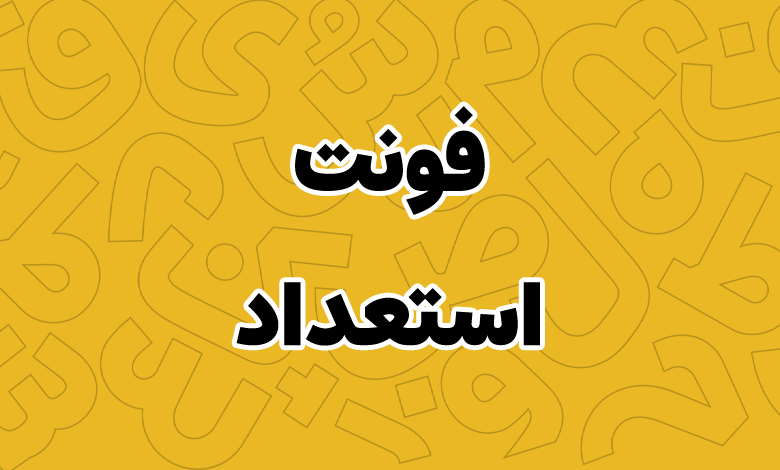
فونت استعداد (Estedad)
فونت استعداد (به انگلیسی: Estedad) در گروه فونتهای رایگان و مناسب متنهای طولانی قرار دارد. این فونت خانوادهدار از چندین وزن متنوع پشتیبانی میکند که به منظور بهینهسازی برای استفاده در متنهای طولانی سایت، نسخه وریبل نیز به آن افزوده شده است.
امین عابدی طراح فونت استعداد است که این قلم را در فروردین ۱۳۹۶ با هدف استفاده برای متون بلند، خصوصا در طراحی صفحات سایت بر پایه فونت سانسریف منتشر کرد. وی جزو توسعه دهندگان فونت ایرانی است که سابقه همکاری با طراحان مختلفی را در زمینه تولید فونت نرمافزاری در کارنامه کاری خود دارد.
در ادامه این نوشته از سایت فونتچی به نقد و بررسی فونت وریبل استعداد خواهیم پرداخت؛ قلمی کاملا رایگان با پشتیبانی از چندین وزن مختلف که میتواند نیاز شما را برای یک فونت مناسب برای سایت تامین کرده و همچنین با توجه به طراحی و ساختاری که دارد، برای مطبوعات مورد استفاده قرار گیرد.
بررسی و دانلود فونت استعداد (Estedad)
فونت استعداد یک قلم خاص فارسی است که ضمن رایگان بودن، امکانات فوق العاده و طراحی عالی را دارد. با استفاده از این قلم میتوانید ساختار حرفهای را به صفحات وب داده یا اینکه در استفاده در مطبوعات و روزنامهها، خوانایی لازم را برای متون به بالاترین میزان ممکن برسانید.
سبک طراحی و وزن فونت استعداد
فونت استعداد بر پایه خط نسخ طراحی شده است. اما تغییراتی که طراح در زوایا، منحنیها، چشمی و خطوط این قلم اعمال کرده ساختار نسخگونه آن را کمرنگ کرده است.
فونت استعداد از ۹ وزن مختلف پشتیبانی میکند که نازکترین آن نسخه Thin بوده و بیشترین وزن را نسخه Black به خود اختصاص داده است. در تمامی وزنها ساختار تمامی حروف به شکل یکپارچه در تمامی بخشها تغییر کرده است که همین موضوع این قلم را به گزینه مناسبی برای طراحی رابط کاربری تبدیل میکند.
پشتیبانی از ۵ زبان متنوع
فونت فارسی استعداد محدود به این زبان نیست. این قلم طبق آخرین نسخه آپدیت شده خود که در صفحه پروژه نیز به آن اشاره شده است، از سایر زبانهای عربی، لاتین و کوردی نیز پشتیبانی میکند که امکان استفاده حرفهای را با توجه به نیاز کاربران ایرانی که دارای فرهنگ عجین شده با سایر ملل هستند فراهم خواهد نمود.
زبانهای عربی و کوردی که بر پایه رسم خط فارسی هستند، پشتیبانی کاملی را در این فونت داشته و هر یک از گلیفهای این زبانها نظیر «ک، ی، ه، ؤ، ئ» که دارای نسخه متفاوت فارسی هستند گلیف اختصاصی خود را به منظور پشتیبانی چندزبانه دارا هستند.
با اینکه در صفحه پروژه اشارهای به زبان اردو نشده است، اما این قلم از گلیفهای زبان اردو نیز پشتیبانی میکند. به سادگی میتوانید گلیفهای خاص این زبان همچون «ﮧ، ﮩ، ے» که نسخه متفاوتی نسبت به فارسی هستند را نیز تایپ کنید.
در تمامی زبانهای خاورمیانه ای تایپ فیس استعداد پشتیبانی کاملی نیز از نظر اعراب دارد. اعراب با ساختار نرم و دوستانه خود همنشینی درستی با «تشدید، همزه، سکون» داشته و وجود چند اعراب کنار هم موجب بههم خوردن ساختار کلمات نمیگردد.
این فونت از زبانهای لاتین نیز پشتیبانی میکند. علاوه بر زبان انگلیسی، سایر زبانهای لاتین که مبتنی بر این رسم خط هستند، همچون زبان فرانسه، ترکی استانبولی یا ترکی آذربایجان که حروفی همچون «ı, ğ, ç, ü» دارای گلیف اختصاصی خود هستند پیاده سازی شده است.
فونت وریبل استعداد با متغیر وزن و کشیدگی
ویژگی منحصر بهفرد دیگر این قلم که در کمتر فونت رایگان وجود دارد، پشتیبانی از نسخه وریبل است. به کمک فونت وریبل استعداد میتوانید بدون نیاز به نصب تمامی وزنهای ۹ گانه این قلم، صرفا با استفاده از یک فایل فونت تمامی این وزنها را در اختیار داشته باشید.
وزنهای این فونت با استفاده از متغیر Weight قابل تغییر هستند. به ترتیب میتوانید با قرار دادن وزن حروف روی مقدار کمترین ۱۰۰ (برای وزن Light) تا مقدار بیشترین ۹۰۰ (برای وزن Black) از تمامی وزنهای این قلم استفاده کنید.
برای استفاده از وریبل فونت استعداد در فتوشاپ کافی است از تنظیمات OpenType این مقادیر را تغییر دهید و برای استفاده در وب نیز میتوانید به کمک کدهای CSS با استفاده از متغیر font-weigh یا wght وزن دلخواه خود را استفاده کنید.
فونت متغیر استعداد یک متغیر دیگر به نام KSHD دارد که به کمک آن میتوانید کلمات را به صورت کشیده تایپ کنید. همانطور که در تصویر بالا مشاهده میکنید، امکان کشیدگی حروف در یک بازه ۱۰۰ تا ۲۰۰ قابل تغییر است.
پشتیبانی از حروف جایگزین
حروف جایگزین فونت استعداد دیگر ویژگی این قلم است که امکان تایپ متفاوت برخی حروف و ترکیبات خاص را در اختیارتان قرار خواهد داد. در نسخههای ضخیمتر این قلم که شاهد افزایش وزن و نمایشیتر شدن ساختار حروف هستیم، استفاده از حروف جایگزین میتواند ظاهر خاصی به برخی کلمات بدهد.
برای مثال همانطور که در تصویر زیر میبینید حروفی نظیر «ک، ی، ه» در حالتهای خاصی که در ابتدا، میانه یا انتهای کلمات باشند ظاهر متفاوتی را فراهم میکنند.
استفاده از این ویژگی زمانی که از فونت استعداد با هدف تبلیغات استفاده کنید، میتواند توجه بیشتر مخاطبان را درپی داشته باشد. حروف جایگزین این قلم محدود به موارد فوق نبوده و شامل ترکیبات مختلف دیگری میباشد که با استفاده از تنظیمات Glyphs در نرمافزارهای گرافیکی میتوانید به همه آنها دسترسی داشته باشید.
پشتیبانی حرفه ای از اعداد فارسی
فونت استعداد از تمامی اعداد فارسی و عربی پشتیبانی میکند. این قلم اعداد عربی همچون «۴۵۶» که شکل متفاوتی نسبت به اعداد «۴۵۶» فارسی دارند را پشتیبانی کرده و دارای گلیف استاندارد برای تمامی زبانهای فارسی، عربی و انگلیسی از نظر اعداد میباشد.
میتونید با استفاده از صفحه کلید استاندارد فارسی اعداد رو مستقیما فارسی تایپ کنید یا اینکه با استفاده از کد js یا فانکشن وردپرس در سایت تبدیل کنید که در مقاله ۶ روش تبدیل اعداد انگلیسی به فارسی در وردپرس توضیح دادیم.